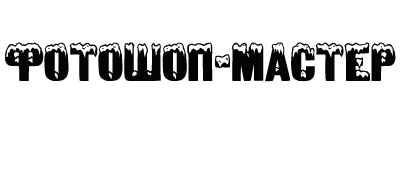
Шрифт - Снежный
Интересный шрифт, который хорошо подходит для работы в фотошопе. Есть поддержка русского языка.
Новогодний)
снежно-снежно
Просто сказочный шрифт
Вот только он не поддерживает некоторые символы. А мне они позарез нужны. Название сайтика с ними. А так все отлично (;